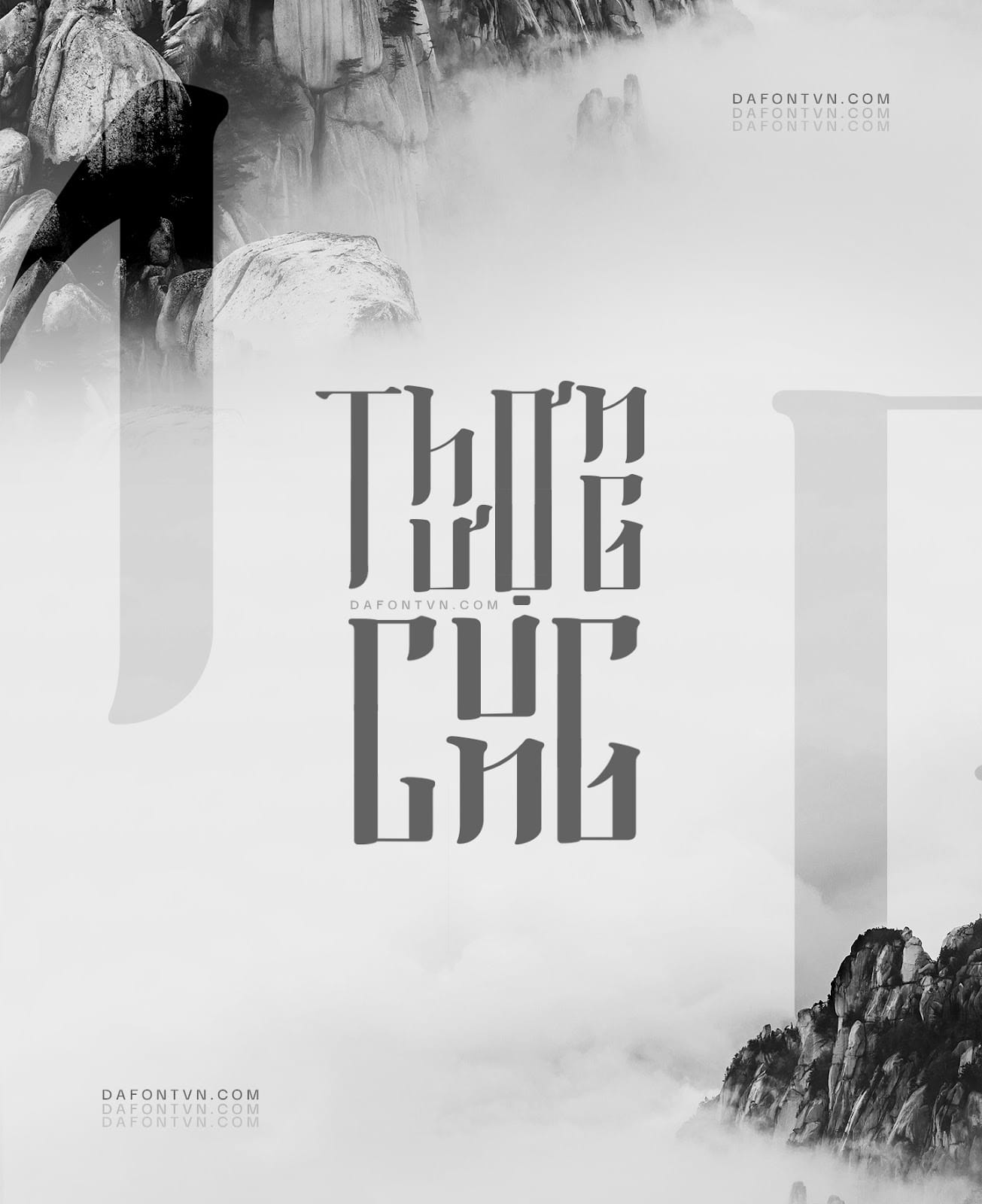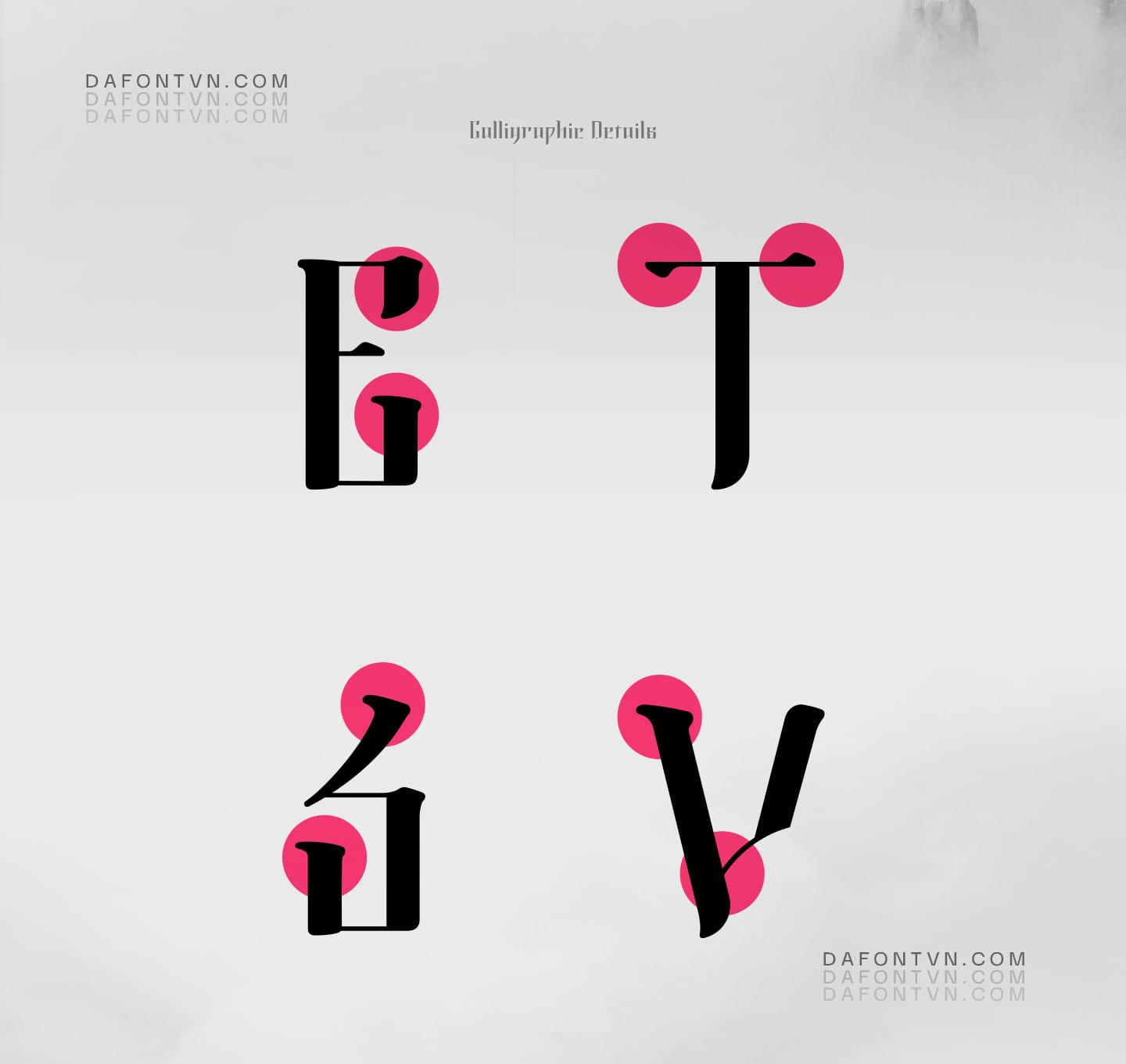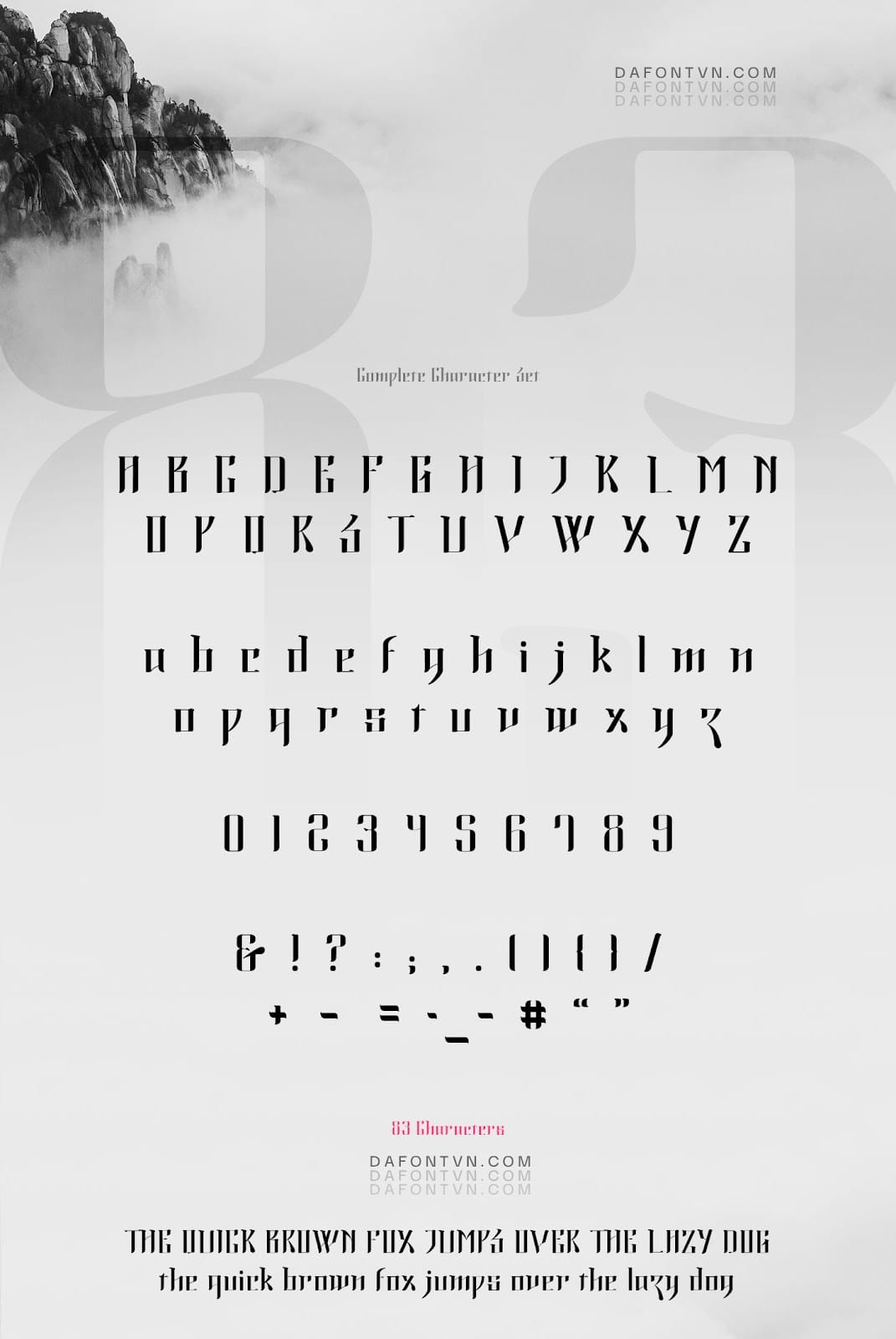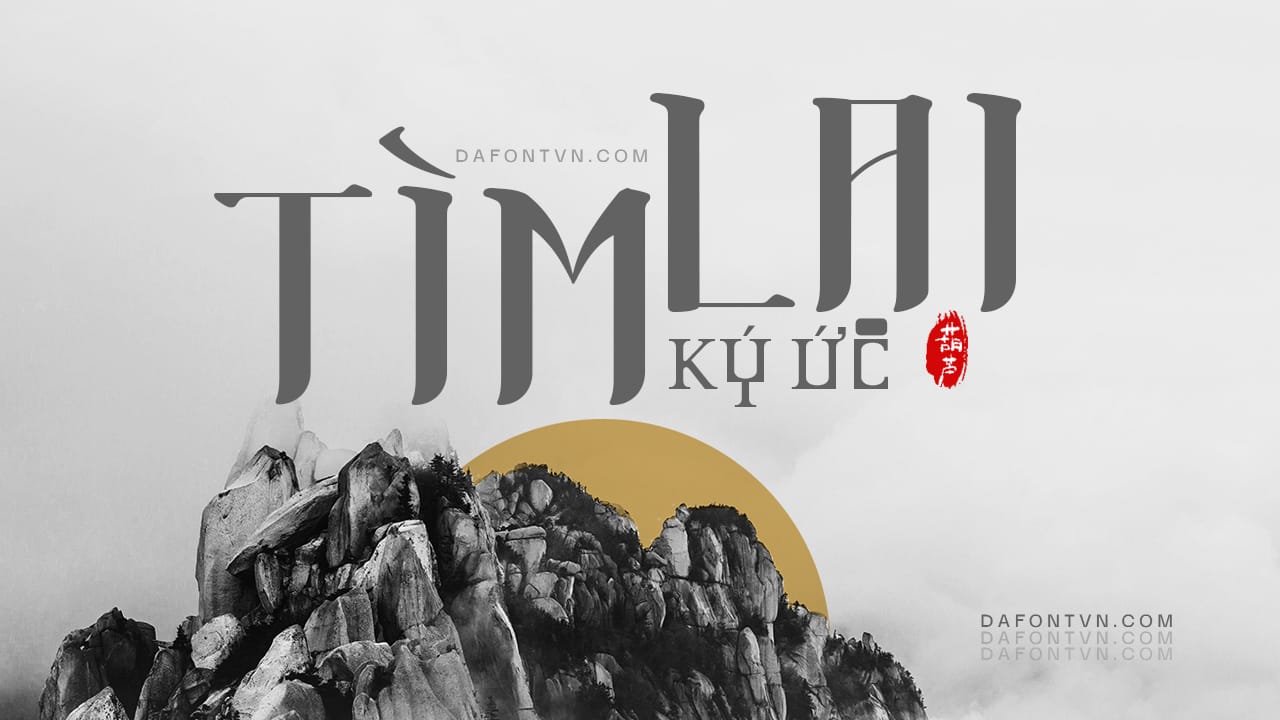
Font Morning Calm Việt hóa được lấy cảm hứng từ các kiểu chữ Hàn Quốc hiện đại và thư pháp truyền thống của Hàn Quốc. Các nét chữ được thiết kế hiện đại kết hợp với các nét bút lông tạo ra sự độc đáo và rất phù hợp để sử dụng cho nhiều thiết kế khác nhau.Tên của font bắt nguồn từ triều đại Jeoson được gọi là Land of the Morning Calm trong tiếng Anh. Morning Calm là một quá trình thiết kế kéo dài 3 tháng để tìm ra sự cân bằng giữa thiết kế kiểu chữ truyền thống và hiện đại, giữa thư pháp và kiểu chữ Hàn Quốc giúp dễ dàng sử dụng cho nhiều mục đích khác nhau với khả năng dễ đọc của nó.